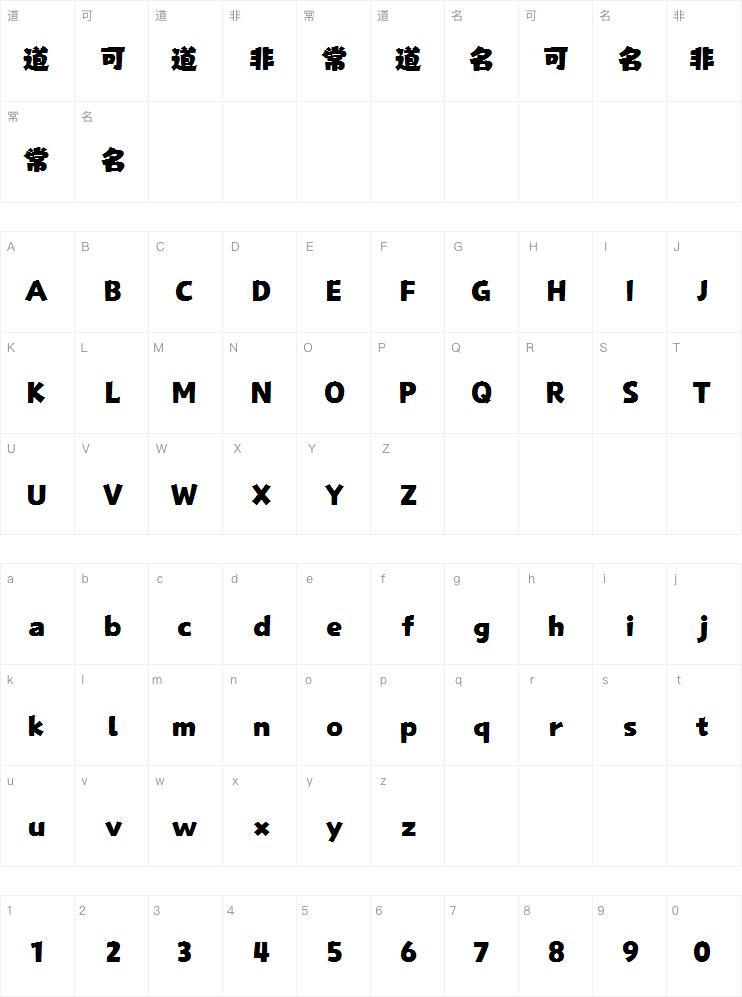
山海自由黑w
山海自由黑,是一款全新的字体,包含汉字9169个,符号200+个。该字体是一款综艺黑体字体,是一款具有强劲视觉冲击力的综艺风格标题字体。字形充实填满整个字框,造型硬朗。直线与圆弧的笔画构成坚实有力,拥有宽大的中宫、粗厚且直线化的笔画设计、简洁明了的笔画切角,带来强有力的视觉冲击效果。该字体在综艺黑体的基础上做了诸多创新,结构区别于传统黑体的规规矩矩,增加俏皮性和随意性,使得该字体既有着端肃的凝重,又有着流动的美感。在正式用字场合落落大方,在日常使用环境中不失亲切友好,能够在保留综艺黑体基本特征的基础上更能适应当下时尚潮流的需要,助力各大新产品夺取标题主战场。